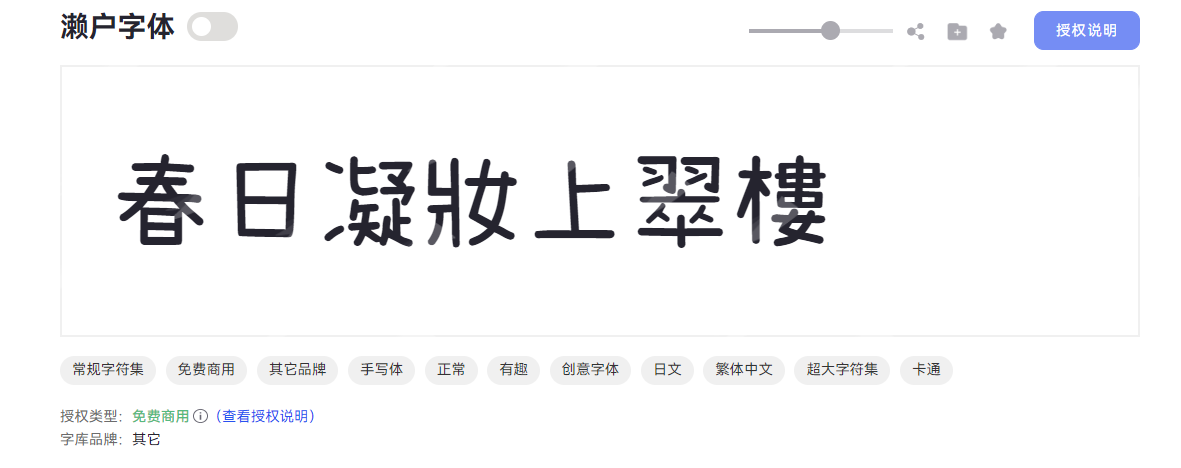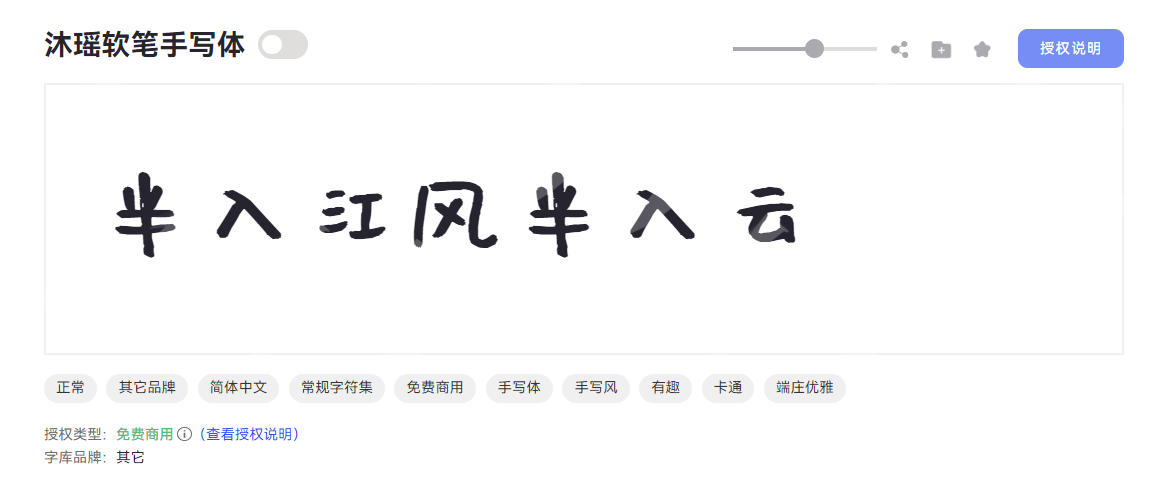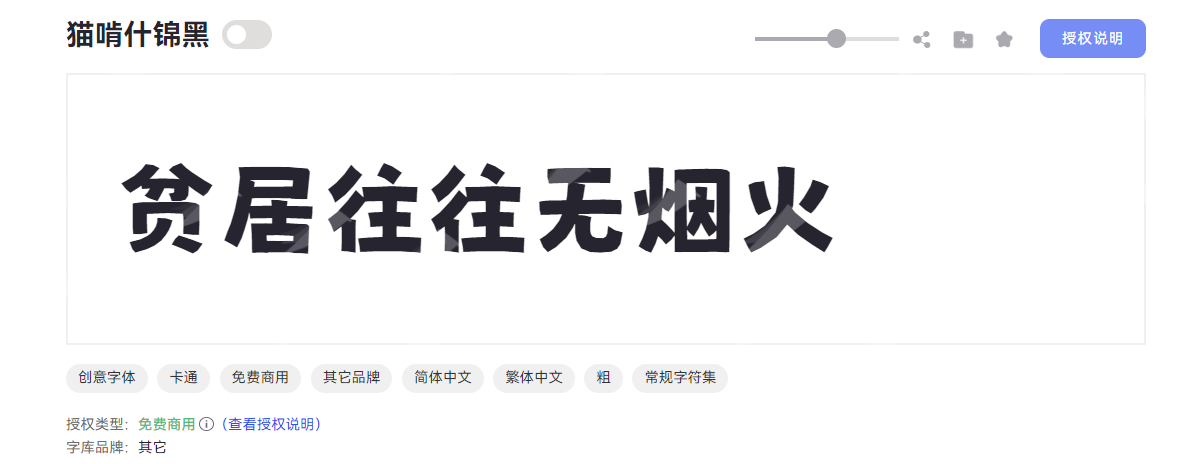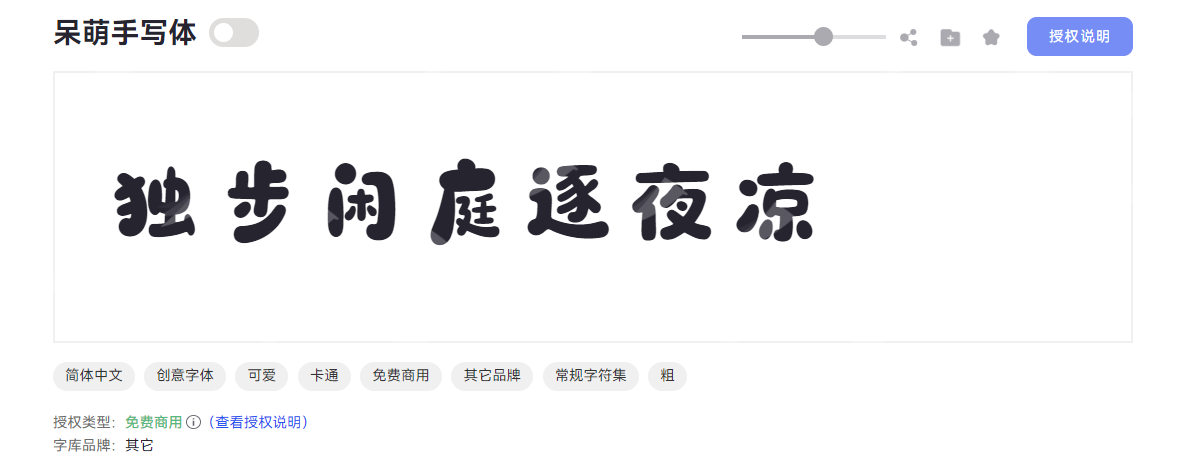
免费商用活泼字体去哪里下载?8 款俏皮中文 + 英文字体实测汇总
你是不是也经常面临这样的问题,好不容易设计有了新灵感,翻遍字体列表也就那几种字体,要么过于正经,要么过于死板。去网上搜集活泼字体,结果广告弹窗比字体还多,下载了还不一定能用,还不知道有没有版权问题。其实这些问题都非常容易解决!字由一个网站全都能搞定,点一下自己想要的风格就能筛选出一堆合适的字体,简直就是字体管理神器。接下来,本文就给大家推荐 8 款免费商用的活泼字体,中文英文都有,亲测超实用!
一、活泼中文字体推荐
1.濑户字体
字体风格:一款兼具创意与手写质感的卡通趣味字体,手写笔触自然不造作,自带“好人缘天然呆”的亲和力,为作品注入温暖活力。
字形特点:濑户字体以修长舒展为基调,重心略向上提升,搭配适中的中宫设计,让字符既显灵动又不失平衡感。笔画末端采用可爱圆头造型,圆角处理柔化了线条棱角,虽整体粗细均匀却透着纤细轻盈的质感,卡通趣味扑面而来。独特的笔画断开设计避免了连笔的繁复,反而让每个字符更显清爽利落
适用场景:一般用于儿童读物内页、萌宠品牌/儿童品牌标识、可爱主题的社交媒体配图、儿童活动区门牌等。
2.沐瑶软笔手写体
字体风格:一款兼具卡通趣味与端庄优雅气质的手写体字体,以灵动手写风为核心。
字形特点:沐瑶软笔手写体在字形结构上展现出独特美感,修长的字型形态搭配居中的重心与适中的中宫,整体视觉平衡且舒展。笔型融入圆润弧度设计,让字体自带温暖柔和的质感,避免了传统手写体的呆板感。 值得注意的是。另外,笔画断开的连接方式,还原了手写书写时的自然停顿感,使每一笔都似随笔尖流转而生。
适用场景:手掌排版、玩具包装设计、萌宠海报标题、手作店铺门牌等。
3.猫啃什锦黑
字体风格:一款主打创意卡通风格的粗体方正字体,营造一种活泼鲜活的氛围感。
字形特点:猫啃什锦黑字体字形方正稳重,重心居中带来自然平衡感;笔画融入斜切元素,方头笔触搭配断开式连接,打破传统粗体的沉闷,斜切角度增添灵动韵律,断开处似随手勾勒的线条,让每个文字都像卡通角色般俏皮鲜活。
适用场景:文创设计、儿童读物封面、短视频标题等。
4.呆萌手写体
字体风格:一款以卡通可爱为核心风格的创意字体,以自然书写的温度感与稚拙笔触传递童真趣味。
字形特点:呆萌手写体采用扁宽字形设计,舒展的结构呈现出轻松活泼的视觉张力。粗且均匀的字重让整体轮廓饱满扎实,圆头笔画与断开式连接设计巧妙融合,仿佛孩童用蜡笔随手勾勒,每个字符都透着不刻意的灵动。笔端点缀圆润装饰元素,模拟手绘时的自然弧度;适度墨迹留痕增添手写真实质感,灵动连笔转折则注入跳跃韵律。
适用场景:卡通 IP 、儿童教育物料、节日海报标题等。
二、活泼英文字体推荐
1.WestSide
字体风格:一款自带萌趣属性的卡通风格英文手写体,融合可爱与有趣的设计语言,有效传递活泼氛围。
字形特点:WestSide 字形结构修长舒展,重心巧妙上提,搭配宽博的中宫设计,让字母在视觉上既显高挑轻盈。它的笔画以利落的直角线条为骨架,局部融入斜切处理,形成刚柔并济的边缘质感;方头笔画的规整与断开式连接的随性碰撞,在超粗字重的加持下,既保持了粗细均匀的整体协调,又通过笔画间隙的呼吸感避免视觉拥挤,赋予字体独特的节奏与张力。
适用场景:潮流品牌 LOGO 、动画片片头、儿童读物标题、社交媒体创意配图等。
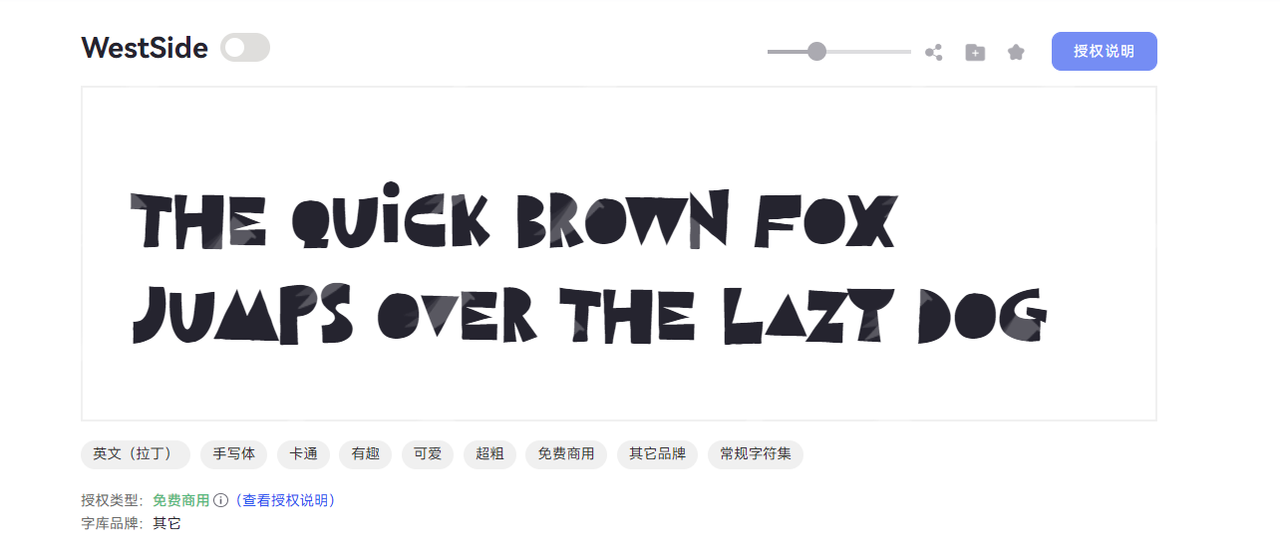
2.Corgi
字体风格:是一款充满趣味的英文手写体,以独特的涂鸦风格展现手写文字的灵动魅力,轻松打造活泼有趣的视觉效果。
字形特点:Corgi采用扁宽的字型设计,字体笔画以圆润笔触为核心,粗重均匀的线条搭配圆头笔画形态,兼具力量感与亲和力。笔画间的断开处理保留了手写的随性特质,让每一个字母都如同即兴创作的涂鸦作品。
适用场景:儿童读物内页、可爱风产品包装、创意标题设计等。
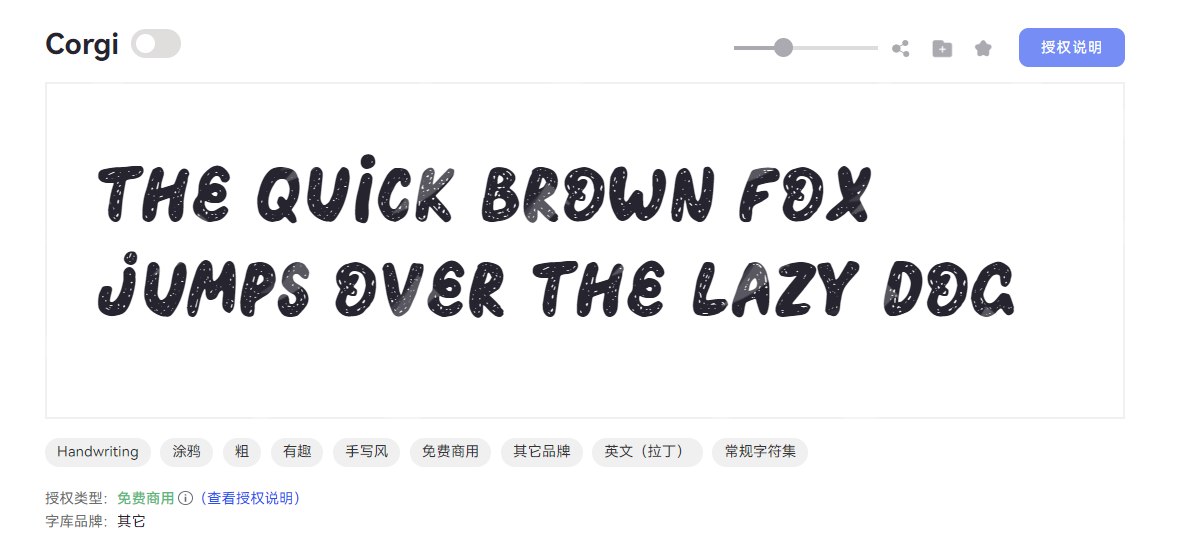
3.Curely
字体风格:是一款充满趣味的英文 Display 字体,以卡通风格为核心设计理念,容易在标题设计中形成独特的视觉焦点。
字形特点:Curely 字形修长,重心偏高,中宫收紧。笔画采用纤细均匀的线条,搭配个性鲜明的斜切装饰元素,尖锋笔画与断开式连接设计形成巧妙对比,给人一种精巧灵动的感觉。
适用场景:创意海报、动画片头、卡通游戏等。
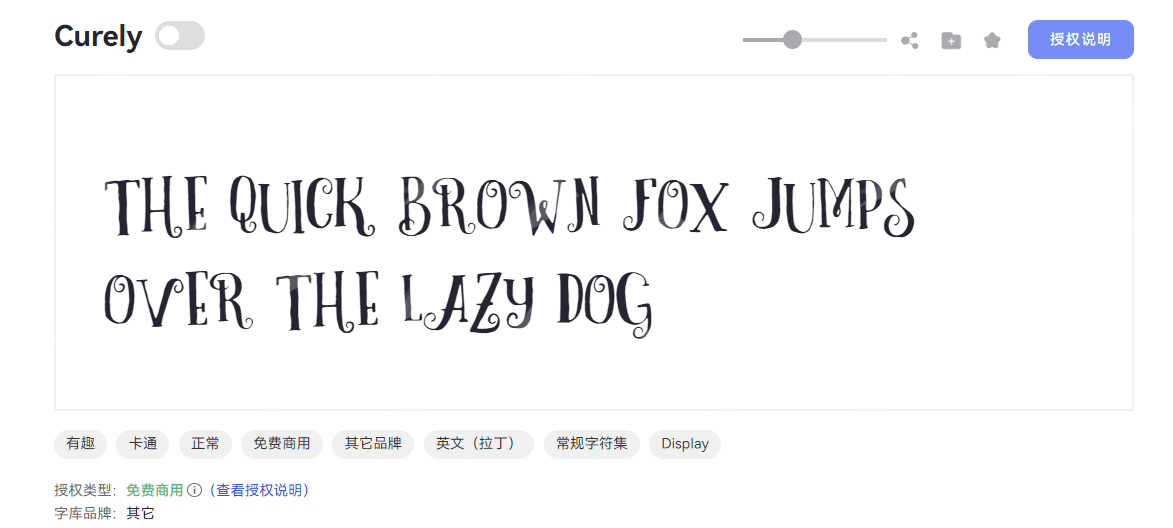
4.Maler
字体风格:一款自带趣味属性的卡通/手写风手写体字体,自带轻盈向上的视觉张力。
字形特点:Maler 的字形结构尤为亮眼,整体修长舒展,搭配偏高的重心设计;在笔型细节上,Maler 笔端融入斜切设计,笔画以利落的尖锋收尾,搭配多处断开的笔画连接,保留了手写字体的随性与温度,又通过几何化的细节增添了设计感,让“手写感”与“设计感”巧妙融合。
适用场景:手写风格文案、手掌排版、儿童产品包装等。